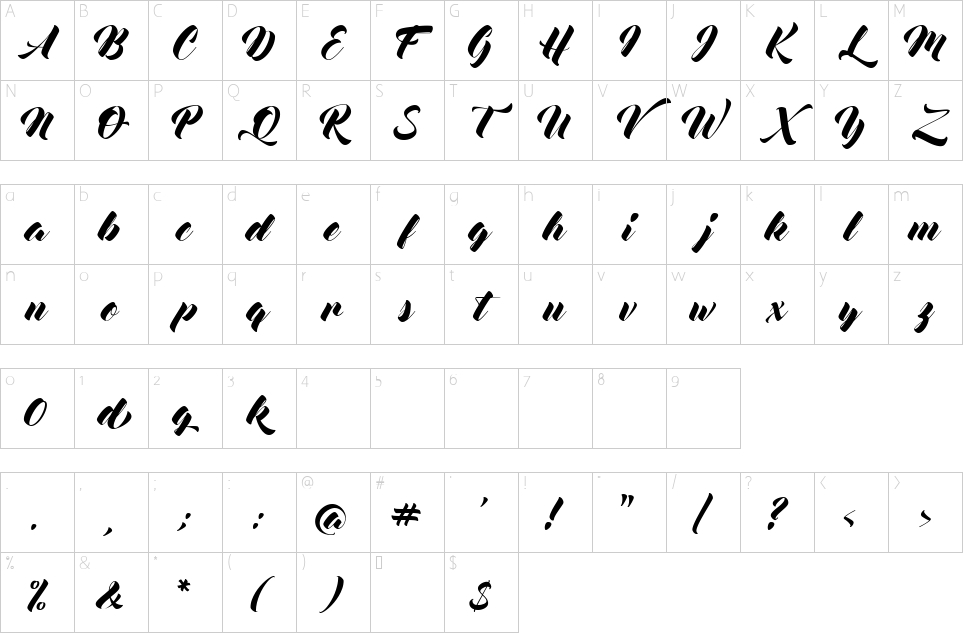
A fonte Mocking Bird é uma escolha perfeita para projetos que buscam um estilo elegante e minimalista. Desenvolvida pelo designer StereoType, essa fonte é versátil o suficiente para adicionar um toque único a qualquer tipo de projeto digital, seja para criar um site atraente ou formatar um texto de e-mail informativo. Com uma elegância simples, Mocking Bird se destaca por sua capacidade de transmitir um sentimento de leveza e frescor, tornando-a uma opção popular para designers que procuram um estilo moderno e atraente para seus projetos. Download gratuita do Mocking Bird font para Windows e Mac, e dê seu projeto um toque único. Embarque nessa experiência e descubra por que esta fonte se tornou uma preferência entre os criativos digitais.